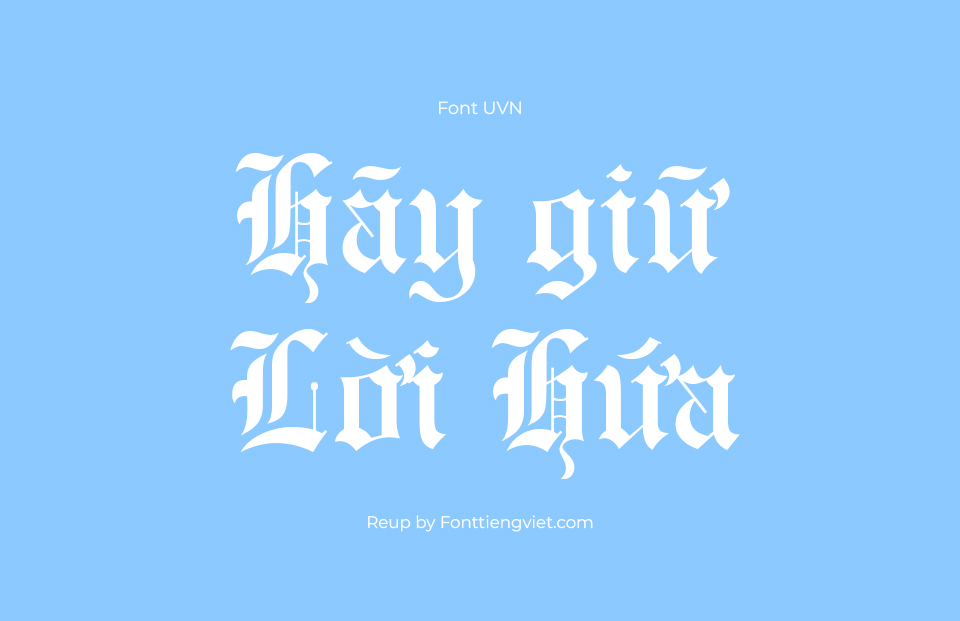
Font Việt Hóa UVN Co Dien
Font Việt Hóa UVN Co Dien: Sự Lựa Chọn Hoàn Hảo Cho Thiết Kế Hoài Cổ
Giới thiệu về Font Việt Hóa UVN Co Dien
Trong thế giới đồ họa hiện đại, việc tìm kiếm một bộ Font Miễn Phí có khả năng truyền tải trọn vẹn tinh thần văn hóa truyền thống là điều vô cùng cần thiết. Font Việt Hóa UVN Co Dien nổi lên như một biểu tượng của sự tinh tế, mang đậm nét hoài cổ và sang trọng. Đây là bộ phông chữ được tối ưu hóa hoàn toàn cho bảng mã Unicode, giúp các bạn học sinh và giáo viên dễ dàng soạn thảo văn bản tiếng Việt mà không lo lỗi font. Với các đường nét thanh mảnh nhưng chắc chắn, bộ chữ này tái hiện lại phong cách in ấn của những thập niên trước, tạo nên một không gian nghệ thuật đầy hoài niệm cho mọi tác phẩm.
Đặc điểm nổi bật của Font Việt Hóa UVN Co Dien
Thiết kế mang đậm dấu ấn thời gian
Điểm khác biệt lớn nhất của Font Việt Hóa UVN Co Dien chính là cấu trúc chân chữ (serif) sắc sảo và tỷ lệ chữ cân đối. Nó gợi nhắc đến những trang sách cổ hoặc những tấm biển hiệu vẽ tay xưa cũ tại Việt Nam.
Tính ứng dụng cao trong học đường và thiết kế
Không chỉ dùng cho trình bày văn bản, bộ font này còn cực kỳ phù hợp để làm bìa báo tường, thiết kế thiệp mời hoặc các slide bài giảng lịch sử. Sự kết hợp giữa nét cổ điển và tính năng việt hóa chuẩn giúp người dùng thể hiện ý tưởng một cách chuyên nghiệp và đồng nhất.
Kết luận về bộ font chữ cổ điển
Việc sở hữu Font Việt Hóa UVN Co Dien sẽ giúp quy trình sáng tạo của bạn trở nên thú vị hơn bao giờ hết. Nếu bạn đang tìm kiếm những bộ Font Miễn Phí, Font Việt Hóa, Font Việt Hóa UVN Co Dien chất lượng để phục vụ cho mục đích học tập hay trang trí, thì đây chính là lựa chọn không thể bỏ qua. Hãy tải ngay để trải nghiệm vẻ đẹp vượt thời gian của con chữ Việt.